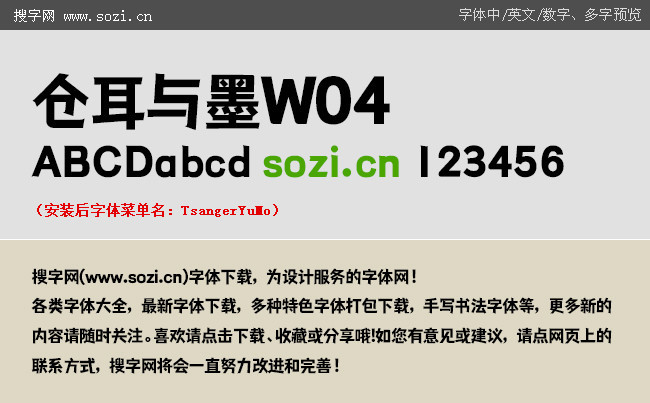
倉耳與墨W04
搜字網(wǎng)提供一款倉耳與墨W04中文藝術字體下載,倉耳與墨字體是由倉耳字庫推出的一款免費字體,共收容漢字6763個,英文及標點等常用字符245個。該字體包含5個字重,風格偏向現(xiàn)代創(chuàng)意字體,強調(diào)厚重與力量,具有醒目、有力和前衛(wèi)的特點。